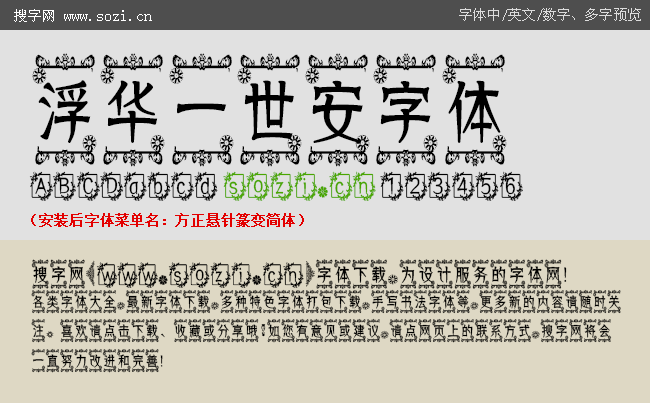
浮華一世安字體
搜字網(wǎng)給大家提供一款很個(gè)性的手機(jī)中文字體下載。修改者給他起了個(gè)性的名字浮華一世安字體,這款手機(jī)字體是在方正懸針篆變字體筆畫間插入了精致的花紋。趣味性實(shí)足,該手機(jī)字體個(gè)性實(shí)足,趣味性強(qiáng),又保持了文字的識(shí)別度,特別適合喜歡手機(jī)字體個(gè)性一些的朋友在手機(jī)上安裝使用。